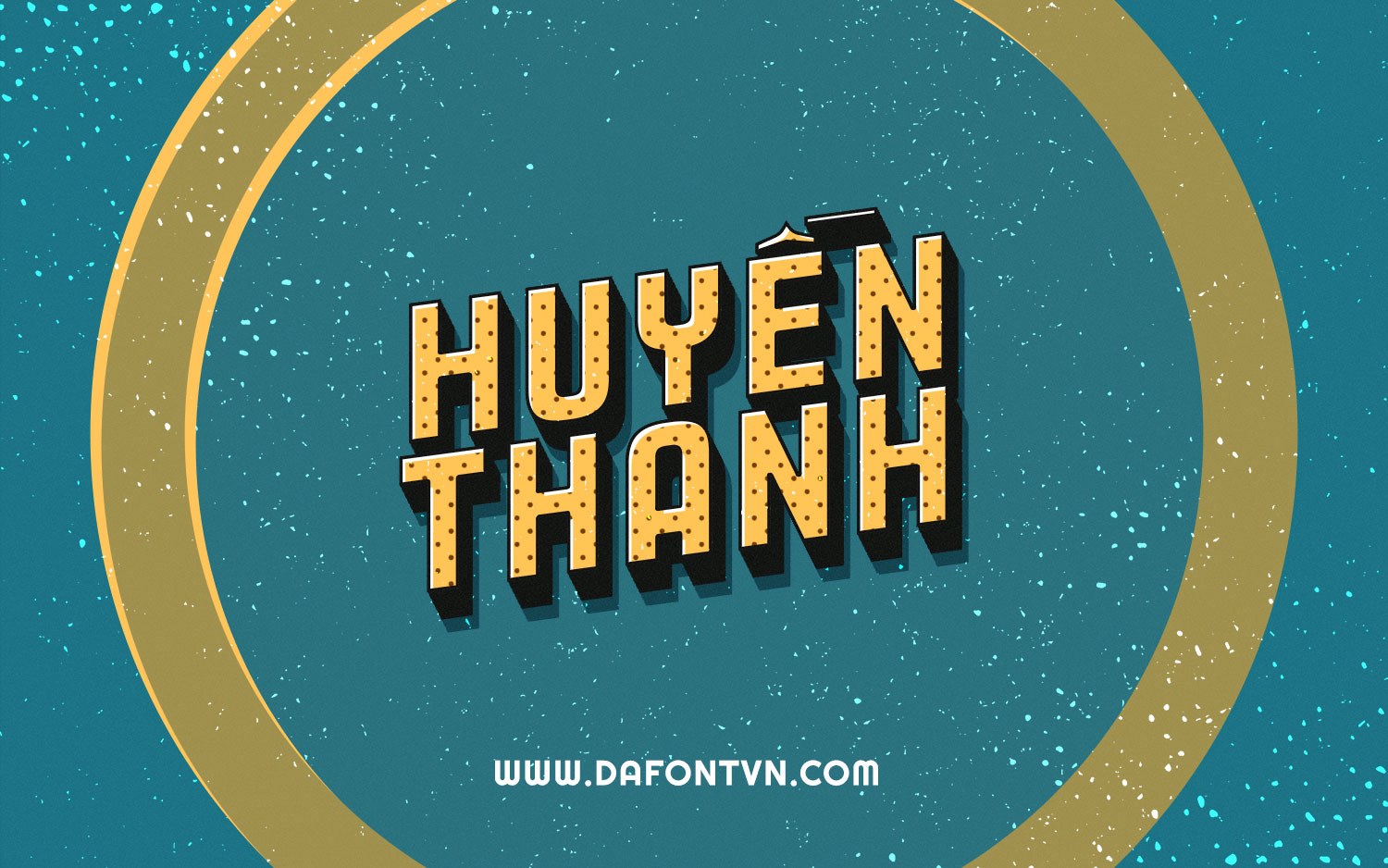
Font iCielBC Expreso Base Việt hóa miễn phí nằm trong bộ font iCiel Nam Kỳ Diễn Ca được Việt hóa và chia sẻ miễn phí bởi iCiel.
EXPRESO được lấy cảm hứng từ giữa thế kỷ trước, các thành phố chính của Colombia – như Bogotá, Medellín và những thành phố khác từ nghệ thuật và thủ công xưa cũ được áp dụng cho xe buýt và các loại ô tô khác phục vụ giao thông công cộng nơi đây.
Font iCielBC Expreso Base Việt hóa